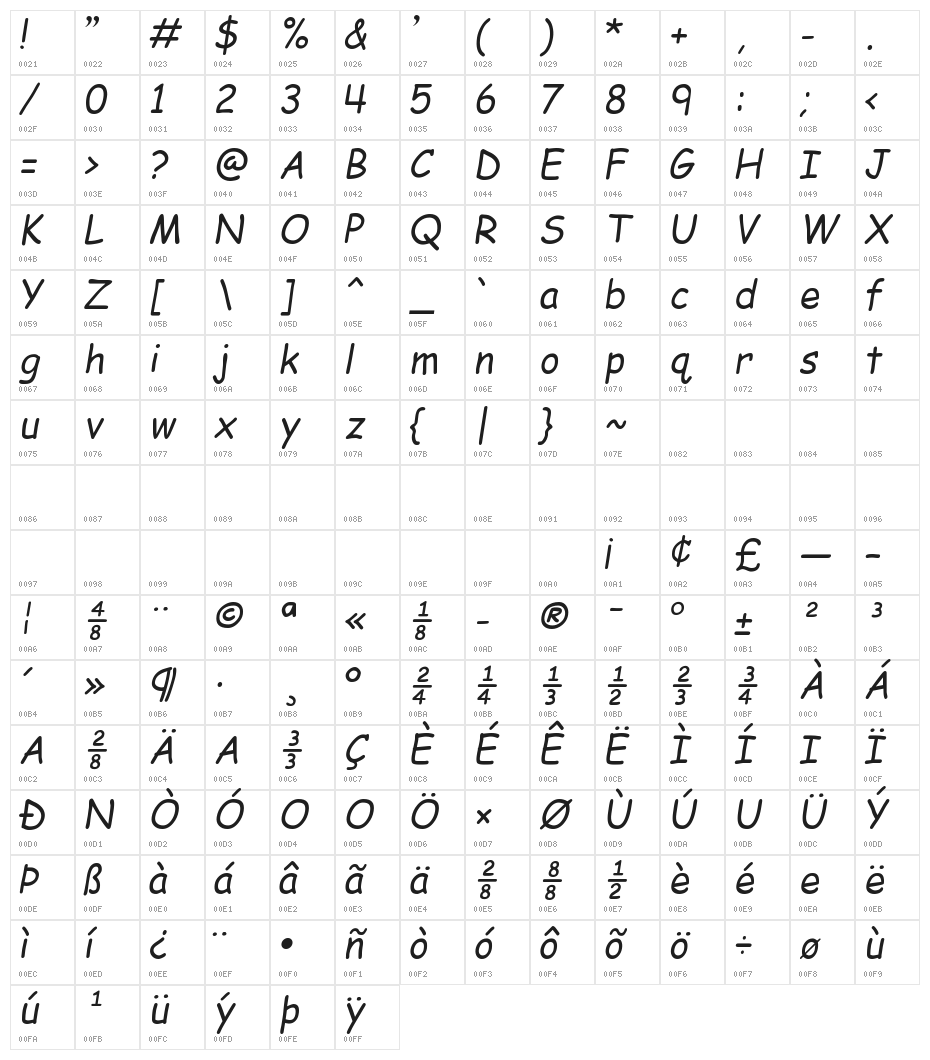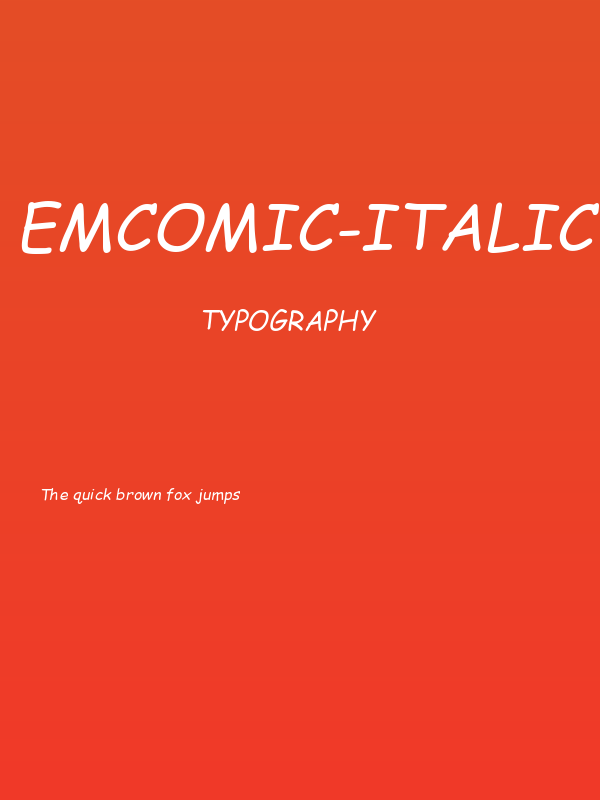
EMcomic-Italic Font
| Gesamtstil | Casual |
| Anwendungsfall | Headlines, Informal text, Comics |
| Vorgeschlagene Projekte | Ideal for comic strips, children's books, casual invitations, and playful branding. |